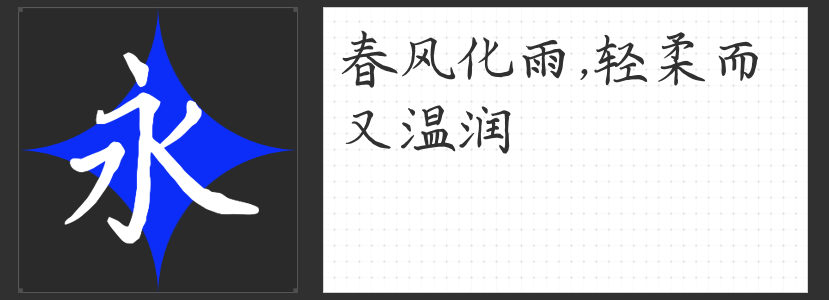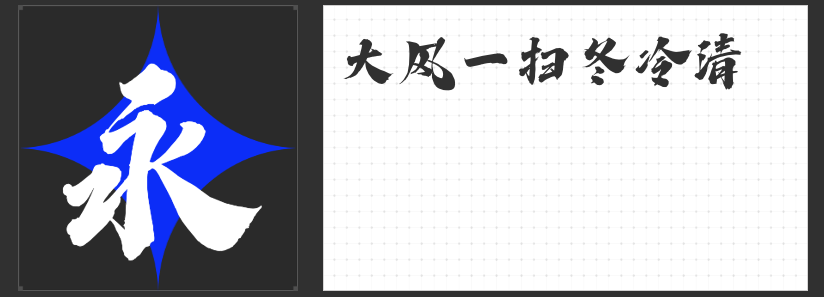
笔墨生辉:四款匠心书法字体赋能设计美学
在设计中,书法字体以其独特的艺术韵味与文化底蕴,成为传递情感、塑造风格的重要元素。今天,我们精选四款风格各异的书法字体,它们不仅展现了传统书法的精髓,更融入了现代设计的美学理念,为包装印刷、广告设计、平面设计等领域带来无限创意可能。
一、 创客贴杨莹凤卿体
创客贴杨莹凤卿体,一款深植传统书法精髓的经典之作。其字形端正大气,笔画稳健有力,每一笔都透露出书法家的深厚功底与对美的极致追求。这款字体既适合用于正式场合的标题设计,也能在文化宣传、古籍复刻中展现其独特的韵味,是设计中传递庄重与典雅的理想选择。
二、 造字侠永刚漆书简繁
造字侠永刚漆书简繁,一款充满创意的毛笔手书字体。其笔画厚重而不失灵动,撇捺之间清晰从容,仿佛能看见书法家挥毫泼墨时的飒爽英姿。框架醒目,字型端庄,整体风格统一而富有变化,无论是包装印刷上的品牌标识,还是广告设计中的视觉焦点,都能完美驾驭,为设计作品增添一抹独特的艺术气息。
三、 高手字斋树高行书
高手字斋树高行书,一款将行书之美发挥得淋漓尽致的书法字体。笔画之间连贯流畅,如同行云流水般自然,展现出书法家高超的技艺与对美的深刻理解。这款字体适用于需要展现动态美感与文化底蕴的设计场景,如书籍封面、艺术展览海报等,能让观者在欣赏设计的同时,感受到书法艺术的魅力。
四、 创客贴劲书体
创客贴劲书体,一款看上去就潇洒不羁的毛笔字体。其笔画刚劲有力,气宇轩昂,仿佛能感受到书法家挥毫时的豪情壮志。这款字体非常适合用于需要展现力量感与个性的设计项目,如运动品牌广告、摇滚音乐节海报等,能让设计作品瞬间充满活力与张力。
这四款书法字体,各具特色,无论是经典稳健、创意灵动,还是行云流水、潇洒不羁,都能为设计作品增添独特的艺术魅力,让设计更加生动、富有感染力。